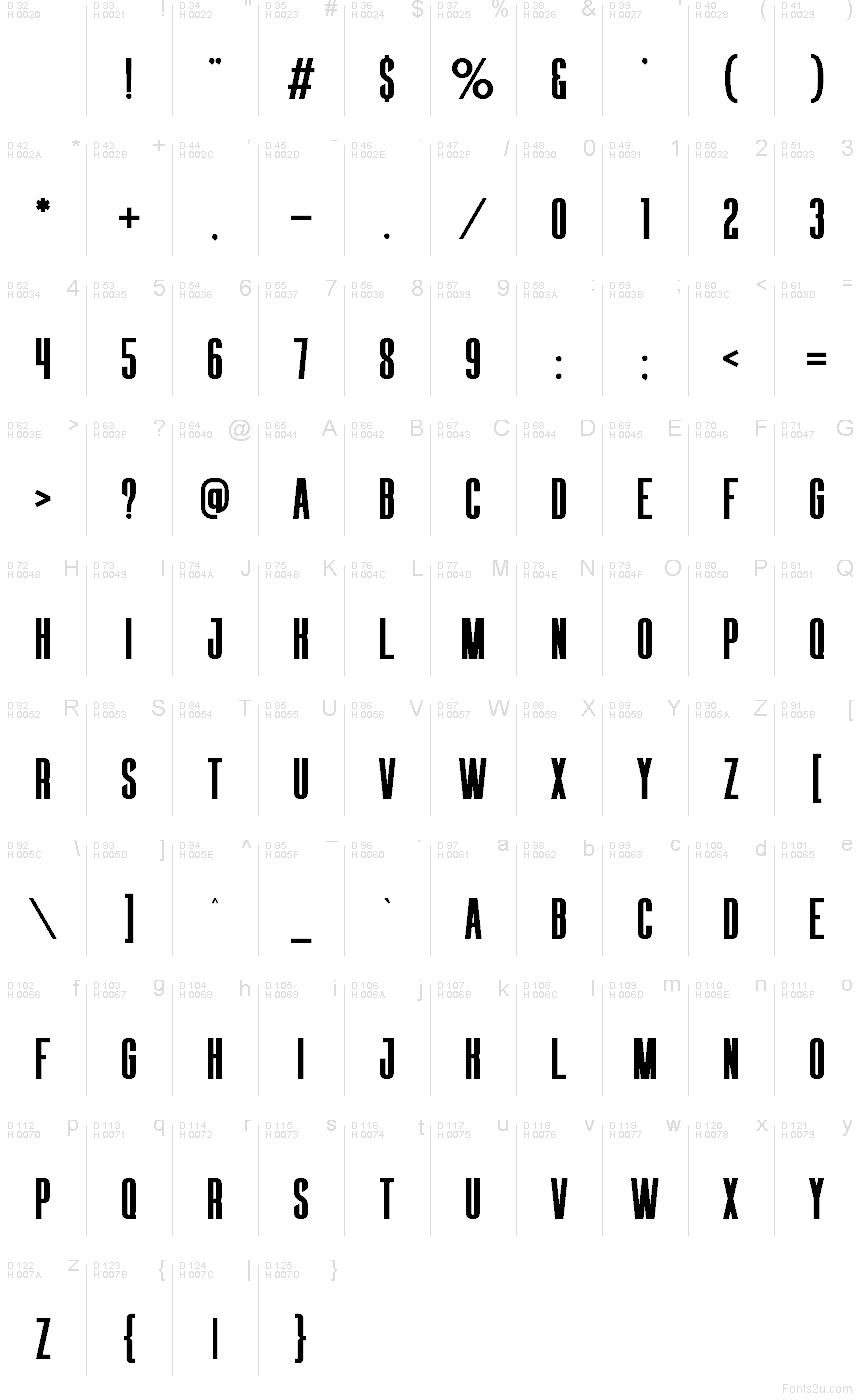
Sansbae de Ermedia Studio es una tipografía sin serifa ultra condensada gratuita con mayúsculas imponentes, trazos verticales marcados y una silueta austera e imponente. Sus proporciones estrechas, su espaciado ajustado y sus cortes abruptos crean un muro denso de letras, mientras que los grosores de trazo cambiantes mantienen las formas individuales nítidas y dramáticas.
La altura exagerada hace eco de las líneas verticales de la fotografía de moda, la arquitectura y la iluminación escénica. Es ideal para campañas de moda, carteles de conciertos y branding de eventos. Los directores de arte de revistas pueden convertir los titulares de portada sobredimensionados en una parte central de diseños editoriales de gran impacto, y no simplemente en un texto neutral.